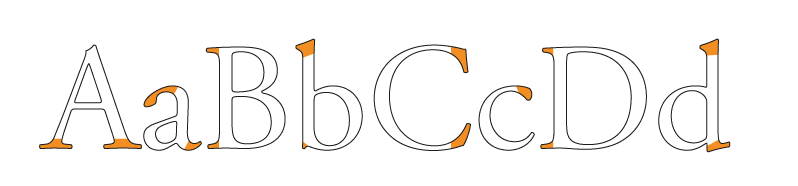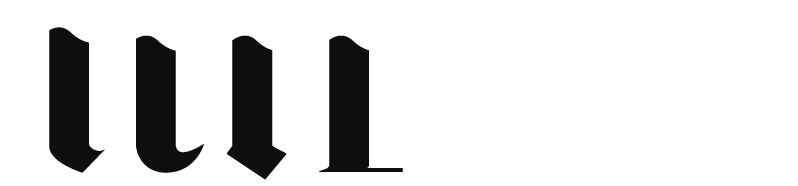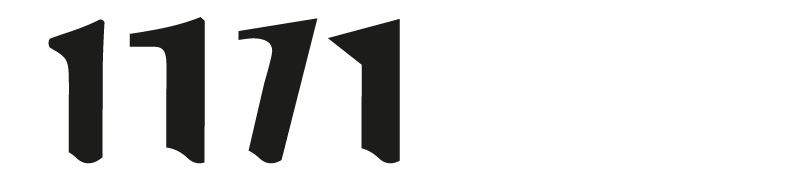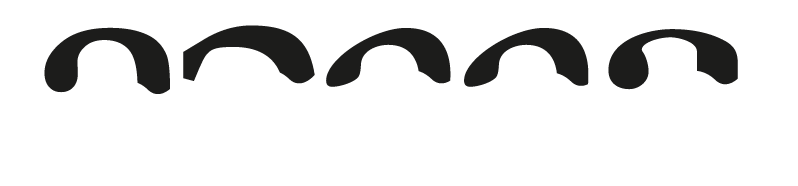
Serife (fr. ‚serif’ = Füßchen) sind kleine – verschieden geformte – Querbalken an den An- und Abstrichen der Schriftzeichen.
Serifenlose Glyphen (sans serif, Grotesk) besitzen diese Eigenschaft nicht – hier wird der Balken gerade oder schräg abgeschlossen.
Es herrscht die Meinung, dass durch den Einsatz der Serifenschrift – aufgrund des mittels Serifen verstärkten Schriftduktus – die Lesbarkeit von Büchern (lange Texte, Belletristik) erhöht wird. Die Untersuchungen der kognitiven Psychologie bestätigen heute lediglich geringfügigen Zuwachs der Lesegeschwindigkeit. Dabei spielen auch andere Faktoren wie Zeilenabstand, Zeichen und Wortabstände, Form und Kerning eine große Rolle. Die digitale Verfügbarkeit von Büchern (eBook, PDF-Datei…) stellt neue Anforderungen an die Technologien (Display, die magere Anzahl der verwendbaren Schriften usw.) und verändert abermals die Lesegewohnheiten der Konsumenten.
Eine der Ursachen für die bessere Lesbarkeit der Serifenschrift mag auch der Mangel an – extra für diesen Zweck konzipierten – serifenlosen Schriften sein.
Im erweiterten Sinn gehören zu den Serifen auch Tropfen und Fähnchen:
Die Serifen sind ein wichtiges Kriterium bei der Klassifizierung der Schriftzeichen.
Häufig kann man eine Schrift anhand der Ausformung der Serife erkennen bzw. zu einer bestimten Schriftfamilie oder -sippe zuordnen.
Es gibt eine Fülle an Möglichkeiten, eine Serife zu gestalten.
In der handgeschriebenen Glyphen nehmen sie häufig die Formen Schnabel, Hacken, Rechteck oder Balken (Linie) ein:
Die Serifen entwickelten sich aus den römischen Inschriften-Versalien.
Das nachstehende Beispiel zeigt Serifen als einen Balken mit leichter Rundung, einer starken Rundung, gekeilt, abgerundet und in der Strichform.
Die Variationen der Serifen können auch folgende Formen einnehmen:
Balkenserife, verklammerte Balkenserife, verkümmerte Serife, gekeilte Serife, ausschwingende Serife, toskanische Serife und (zum Vergleich) serifenlose Endung.
Verschiedene Möglichkeiten der Serifengestaltung der Oberlängen:
Der Tropfen des gemeinen ‚a’ enthält ebenfalls Hinweise für die Bestimmung der Schrift:
Diverse Formen der Serifen der ‚T’ Majuskel.
Schräg, symmetrisch geschrägt und symmetrisch vertikal. Ähnliche Formen tragen E, F, L.